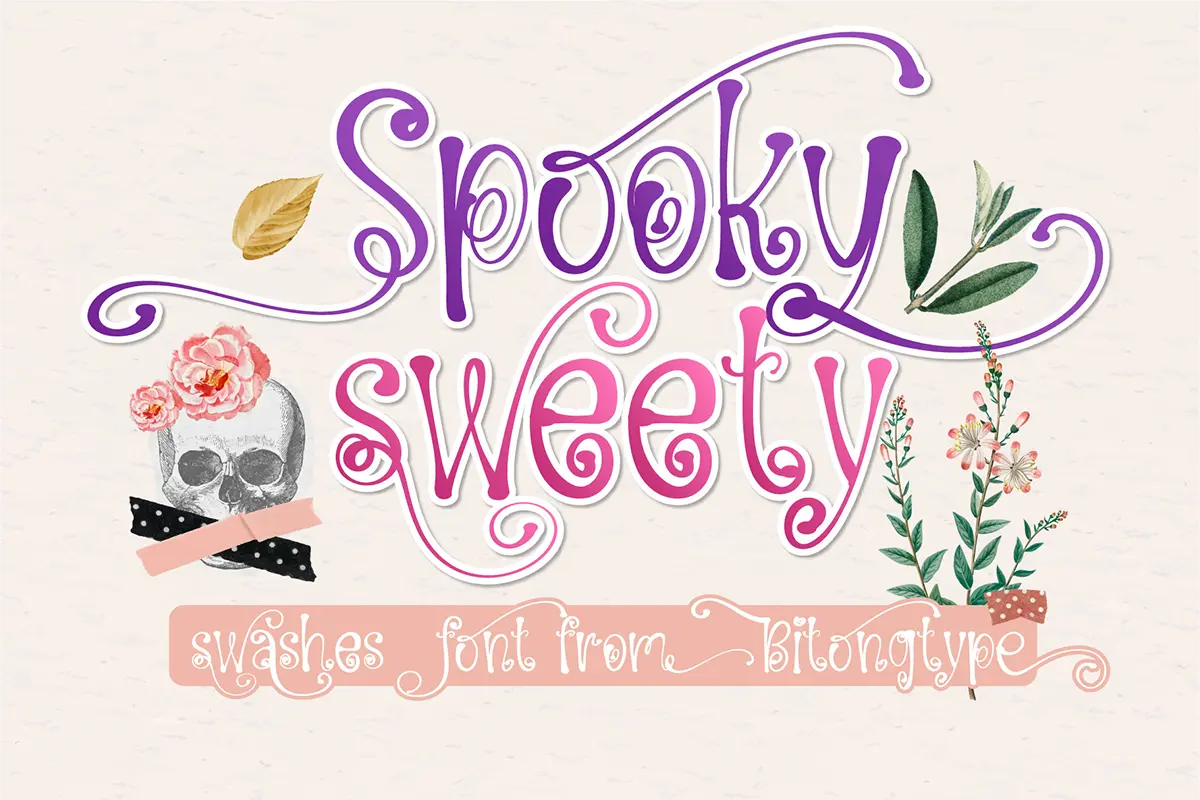
فونت ترسناک شبح وار Spooky Sweety
Spooky Sweety یک فونت فانتزی ترسناک شبح گونه، شیرین و دوستانه است که با سبک طبیعی و منحصر‌به‌فرد خود، برای طیف وسیعی از طراحی‌ها مناسب است. این فونت با حال‌وهوای بازیگوش و لطیف، انتخابی عالی برای پروژه‌های کودکانه، کارت‌های تبریک، طراحی بسته‌بندی، پست‌های شبکه‌های اجتماعی و برندهای خلاقانه است.
✨ ویژگی‌های کلیدی
• ✍️ سبک دست‌نویس با شخصیت منحصر‌به‌فرد
• 🎨 مناسب برای طراحی‌های فانتزی، کودکانه و دوستانه
🎯 مناسب برای استفاده در
• طراحی لوگو، بسته‌بندی و برندینگ شخصی
• کارت دعوت، پوستر، بنر و پروژه‌های چاپی
• پست‌های شبکه‌های اجتماعی و کپشن‌های خلاقانه
• طراحی دفترچه، ژورنال، تی‌شرت و محصولات قابل چاپ
• پروژه‌های DIY، طراحی وب و رابط کاربری